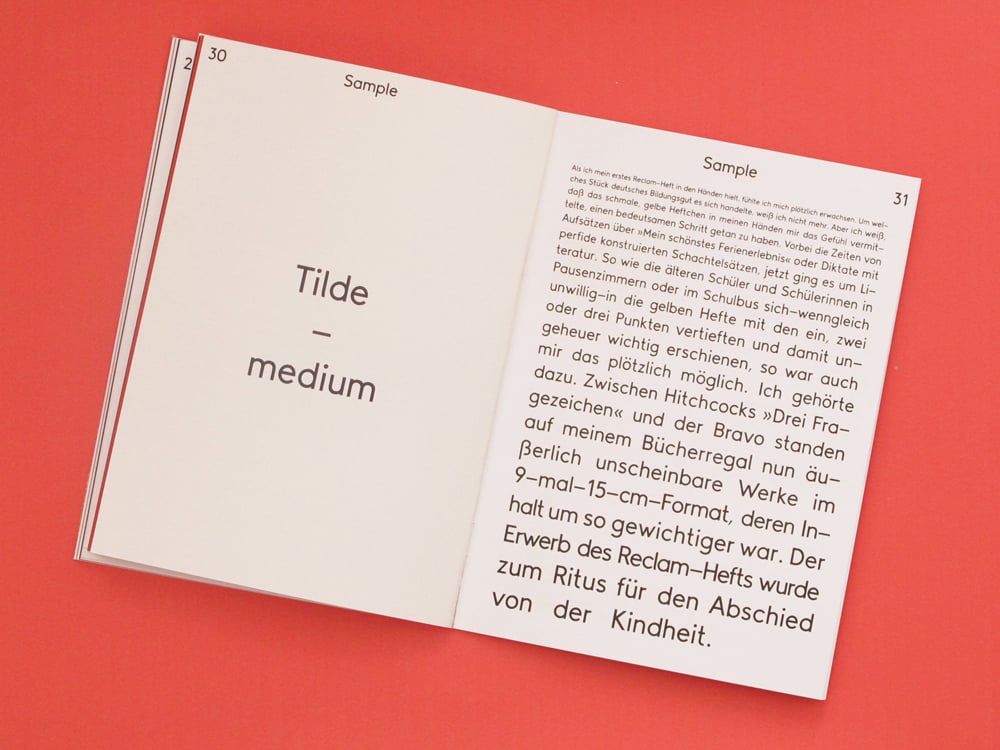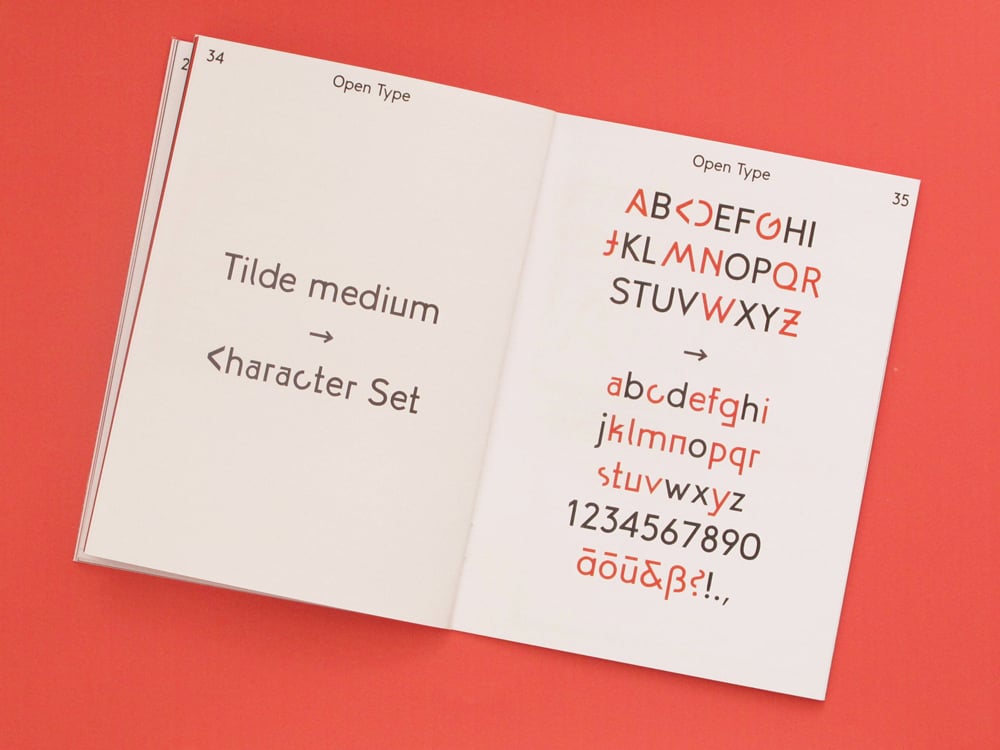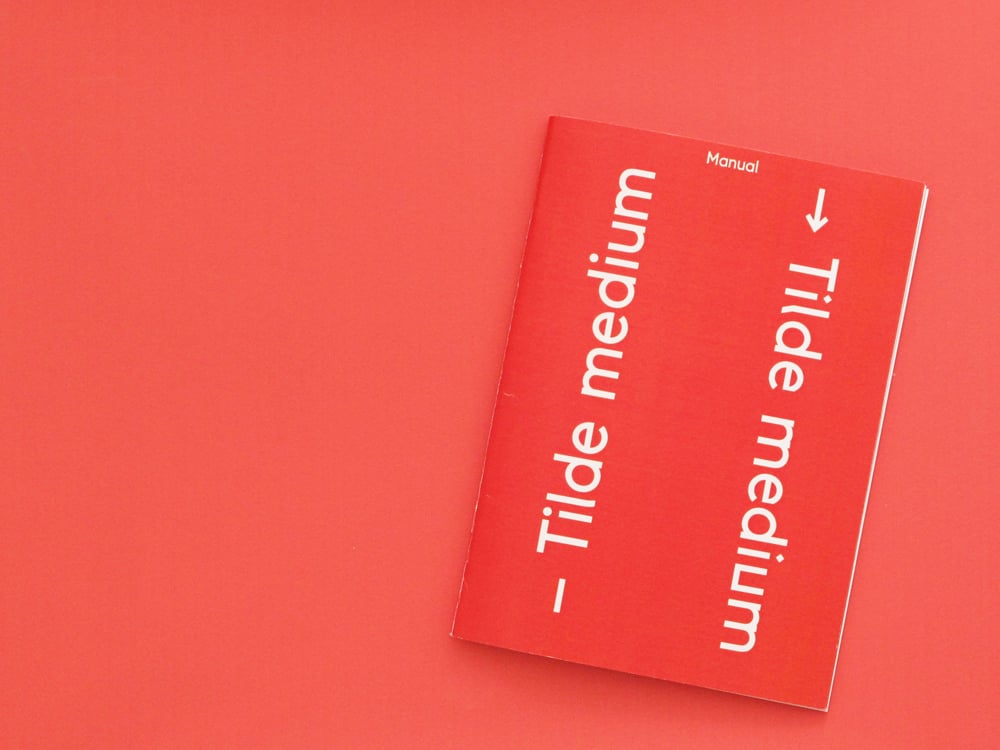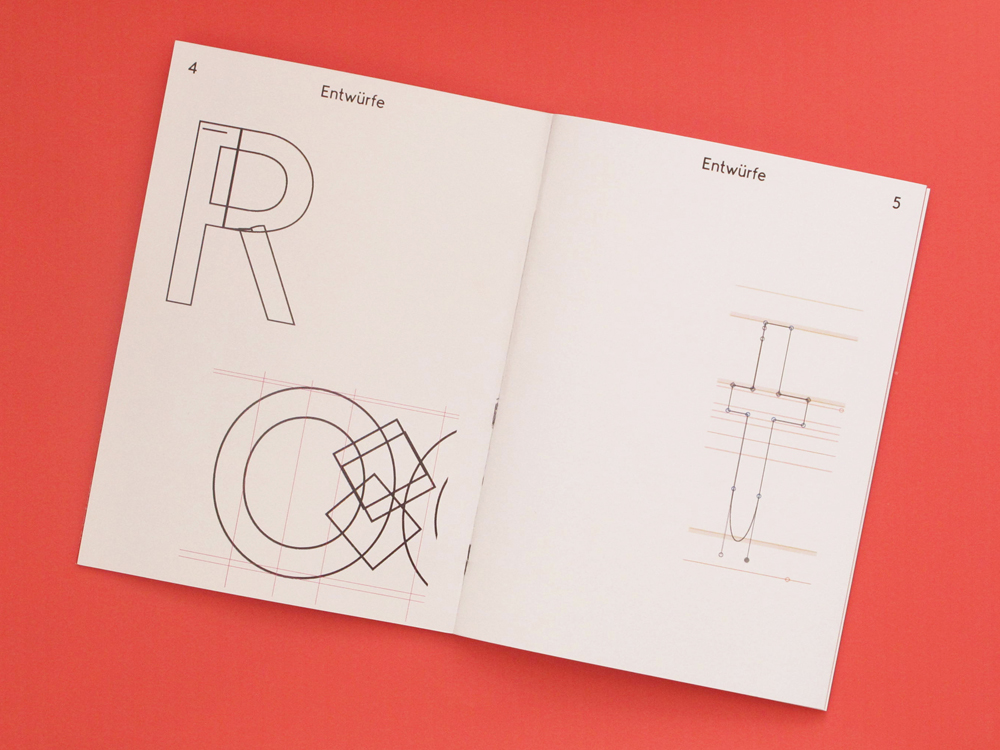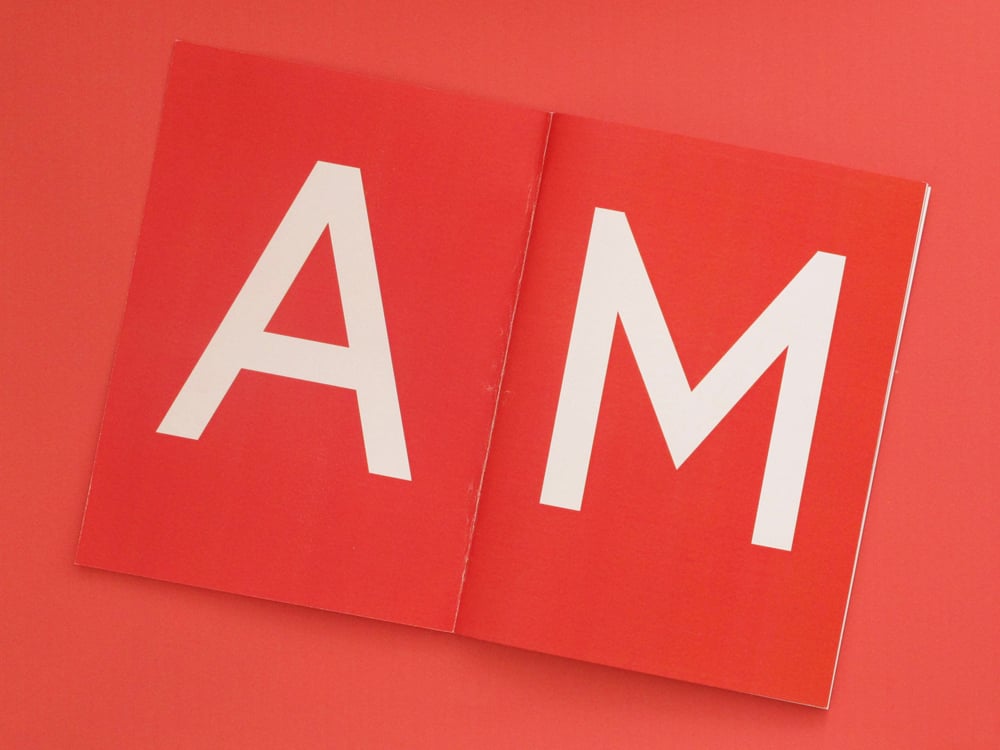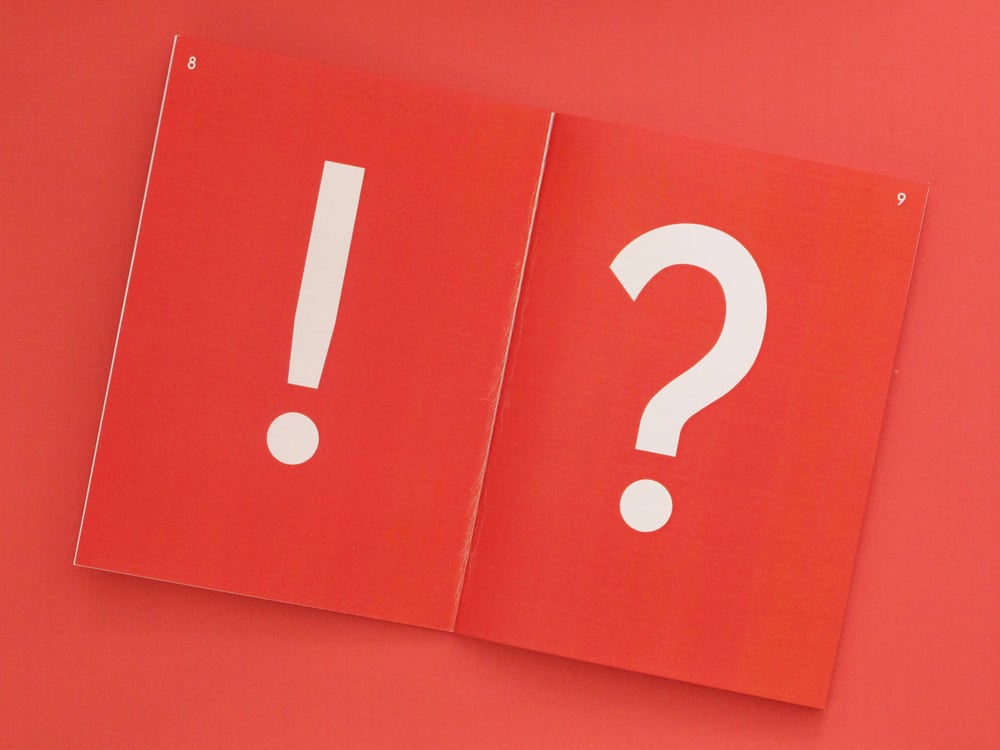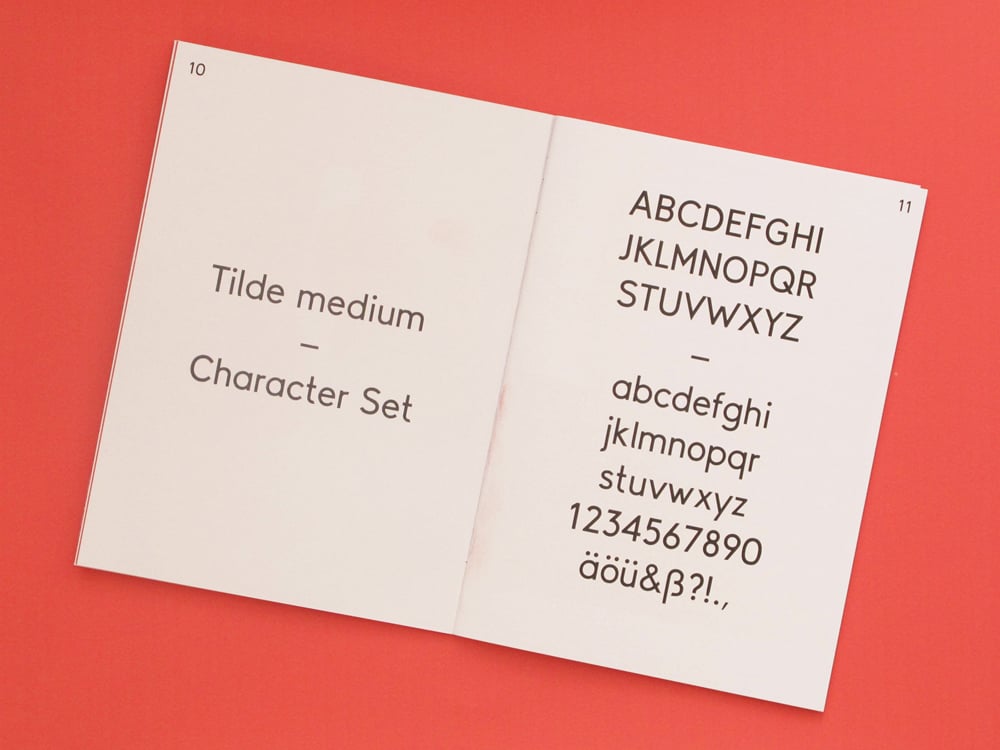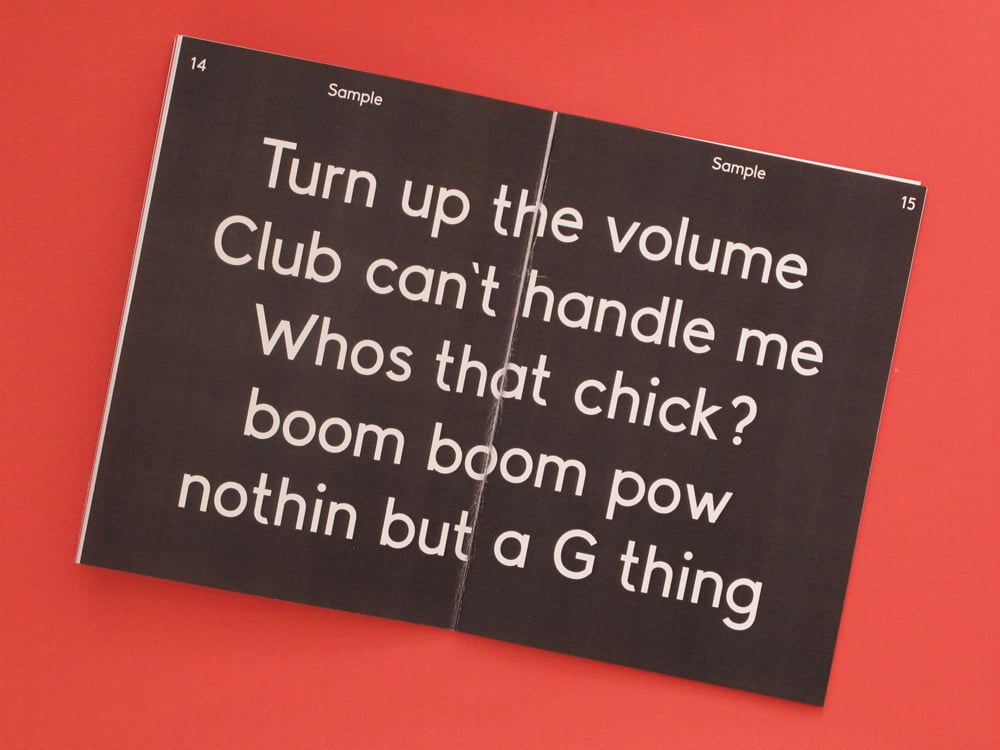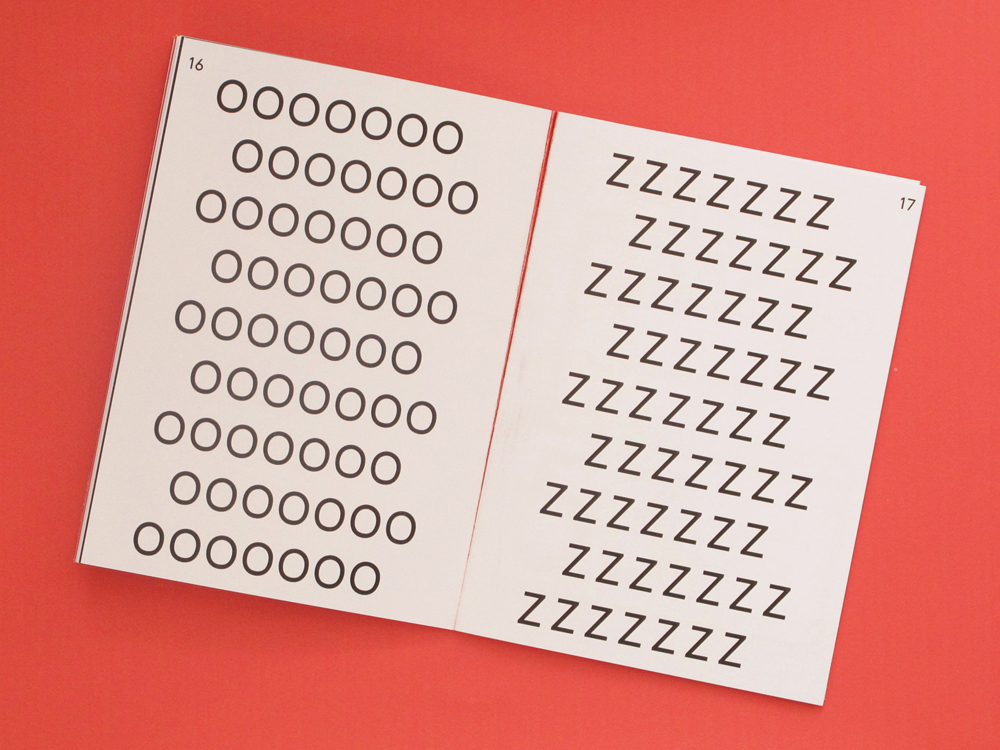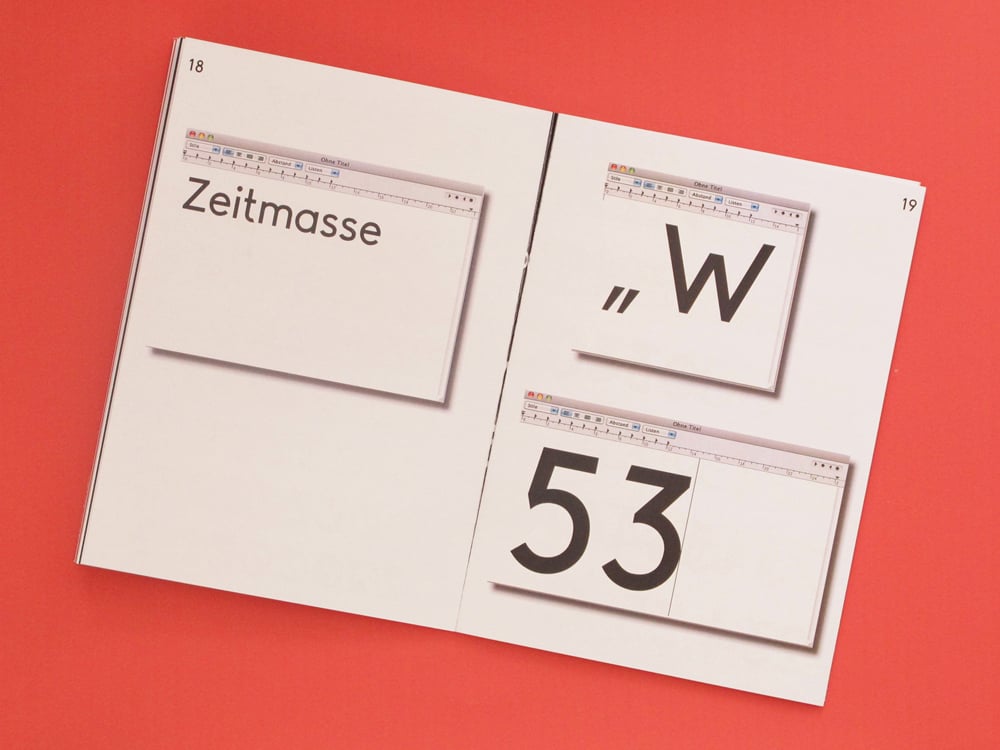
Die konstruierte Schrift Tilde Medium entstand als ein freies Studienprojekt von den Studenten Armin Brenner und Markus John. Grundgedanke war es, eine plakative Display Schrift für Headlines zu entwerfen. Mit ihren geometrischen Grundformen erinnert sie auf den ersten Blick an klassische Groteskschriften aus der Zeit des Konstruktivismus. Auf den zweiten Blick offenbaren sich jedoch eigenwillige Details und Brüche. Tilde medium ist eine voll funktionsfähige Schrift, die eine größere Schriftgröße voraussetzt um gut zur Geltung zu kommen. Auf Anfrage kann die Schrift gerne für Studienprojekte verwendet werden.